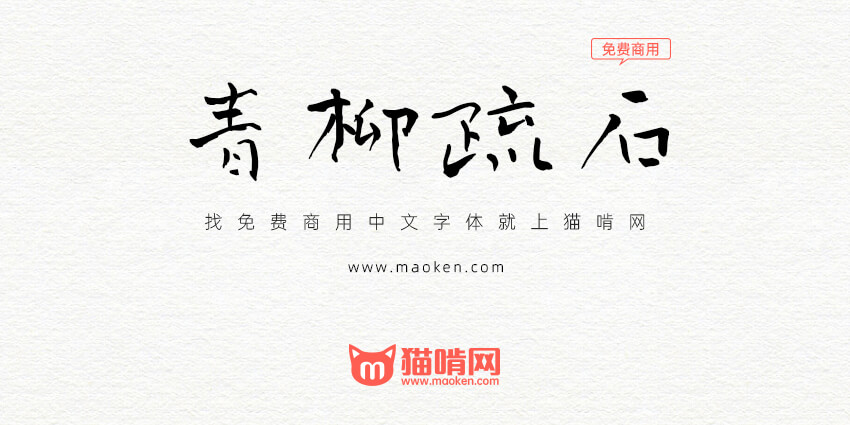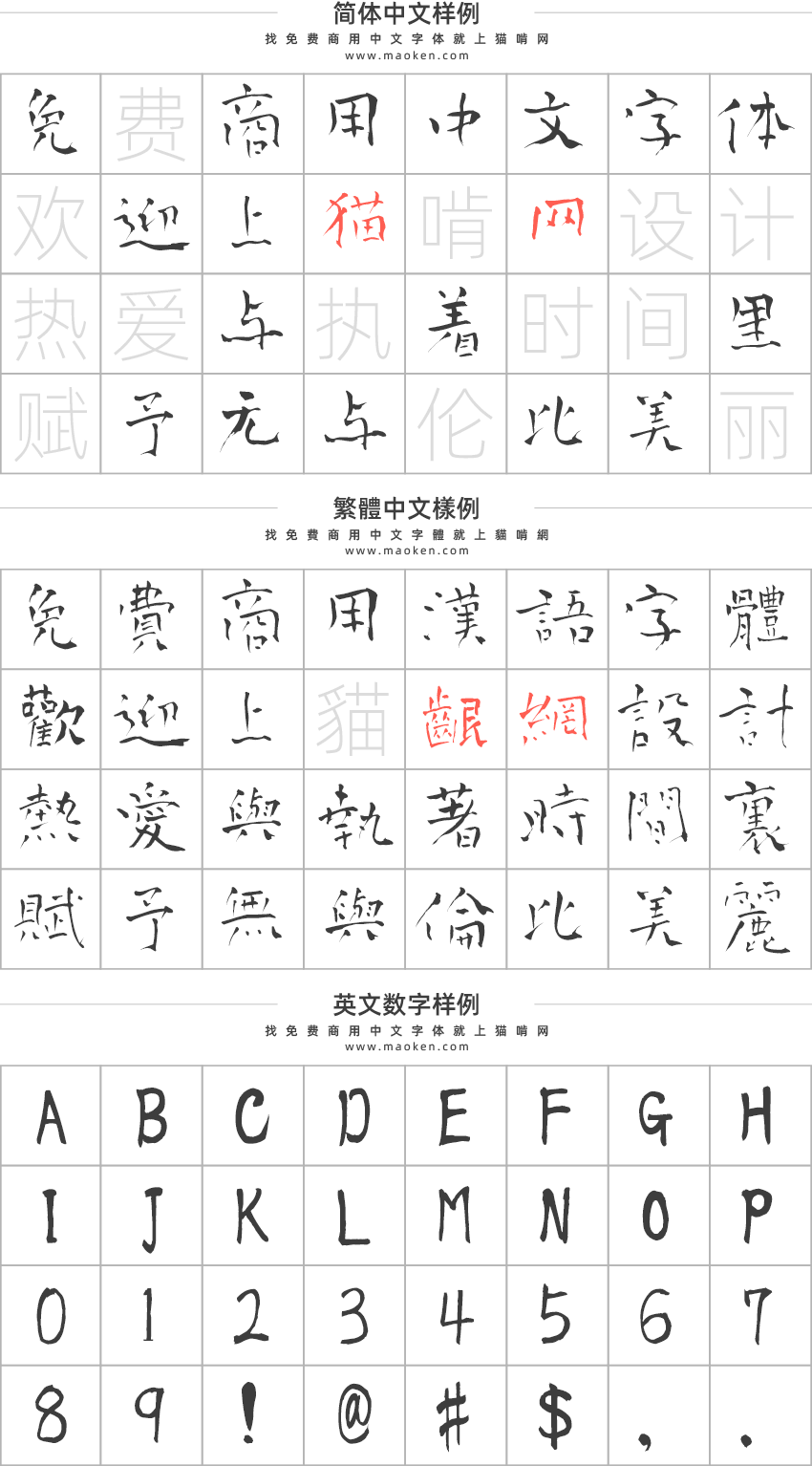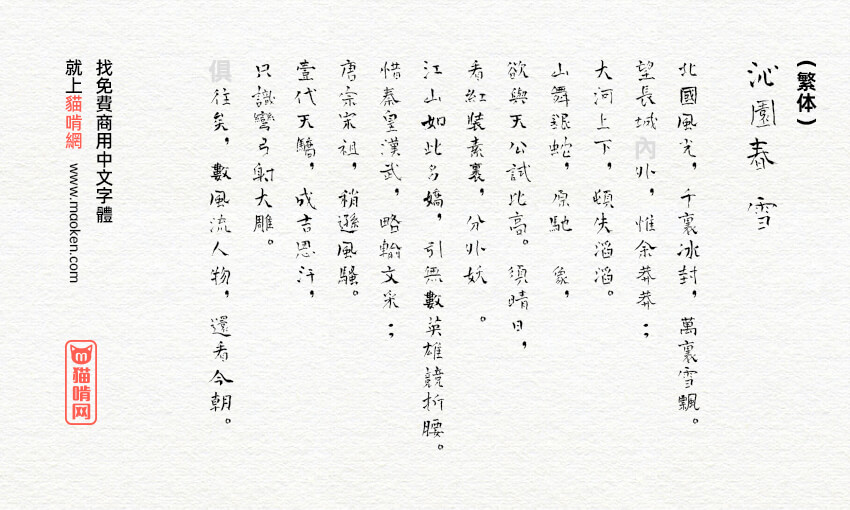
青柳疏石体:日本书法家青柳疏石创作的书法字体
青柳疏石体是日本书法家青柳疏石老师挥毫创作的书法字体,青柳衡山先生负责将其它制作成字体文件。青柳疏石体这款字体看上去歪歪扭扭的极具特色,包含JIS第1水准2965字,第2水准3390字。由于字体采用的日本的JIS标准,所以支持的简体字数不算多,但是繁体却是比较齐全的。